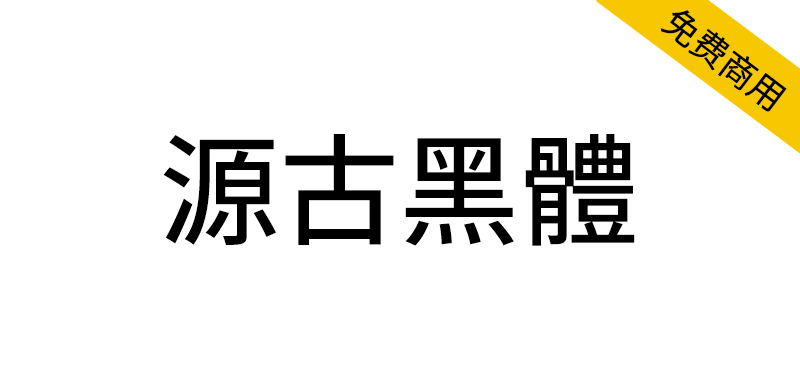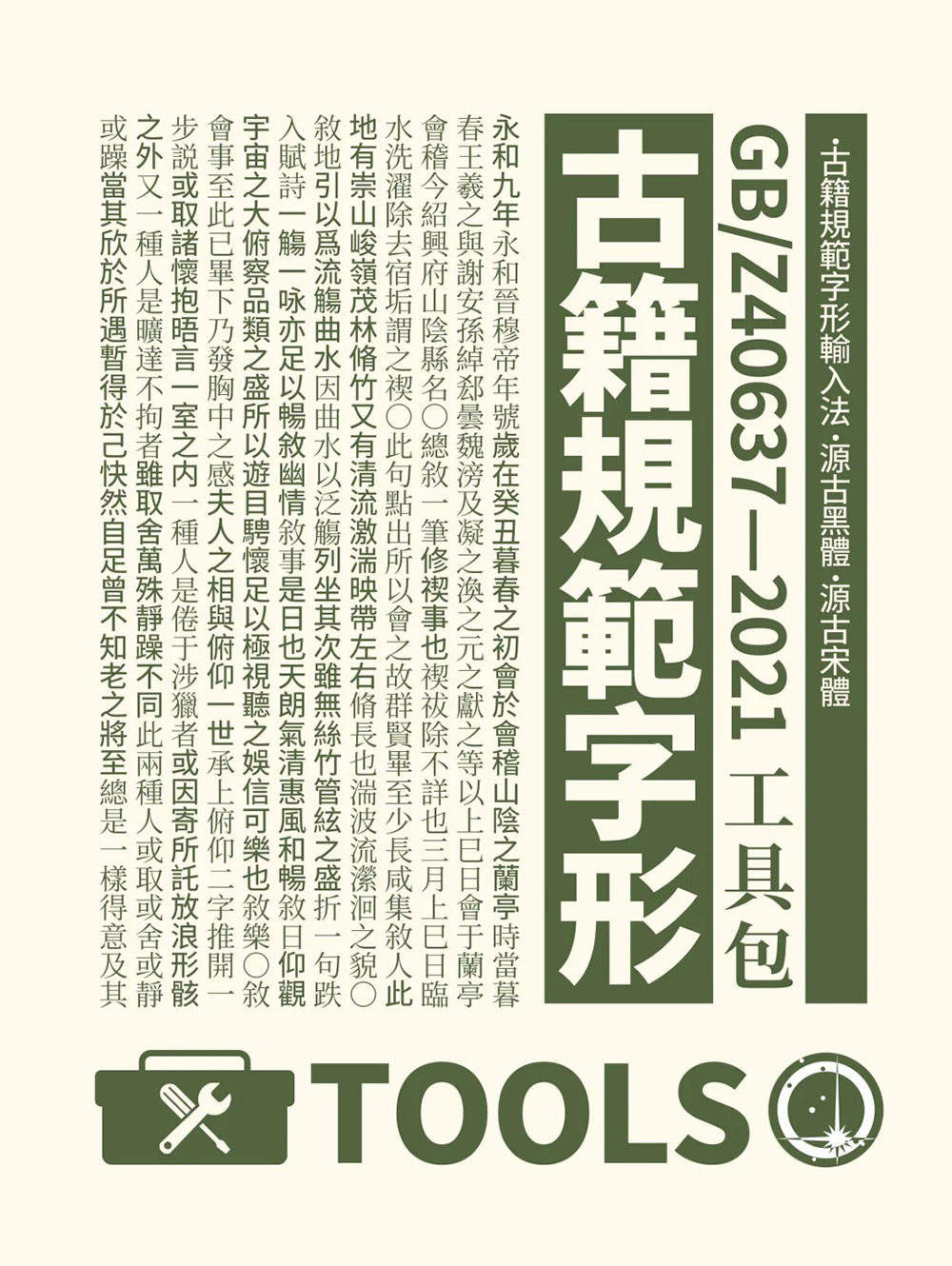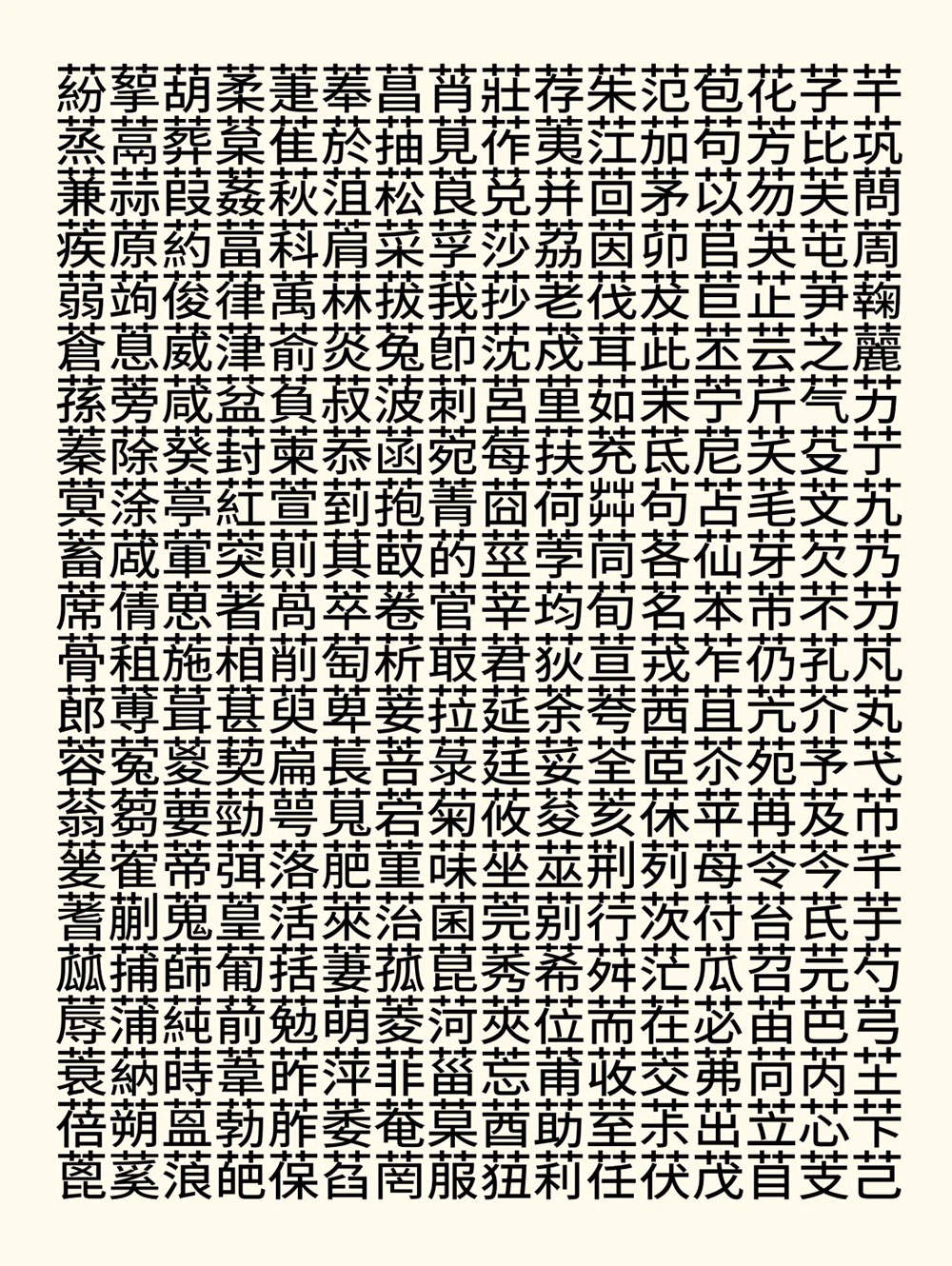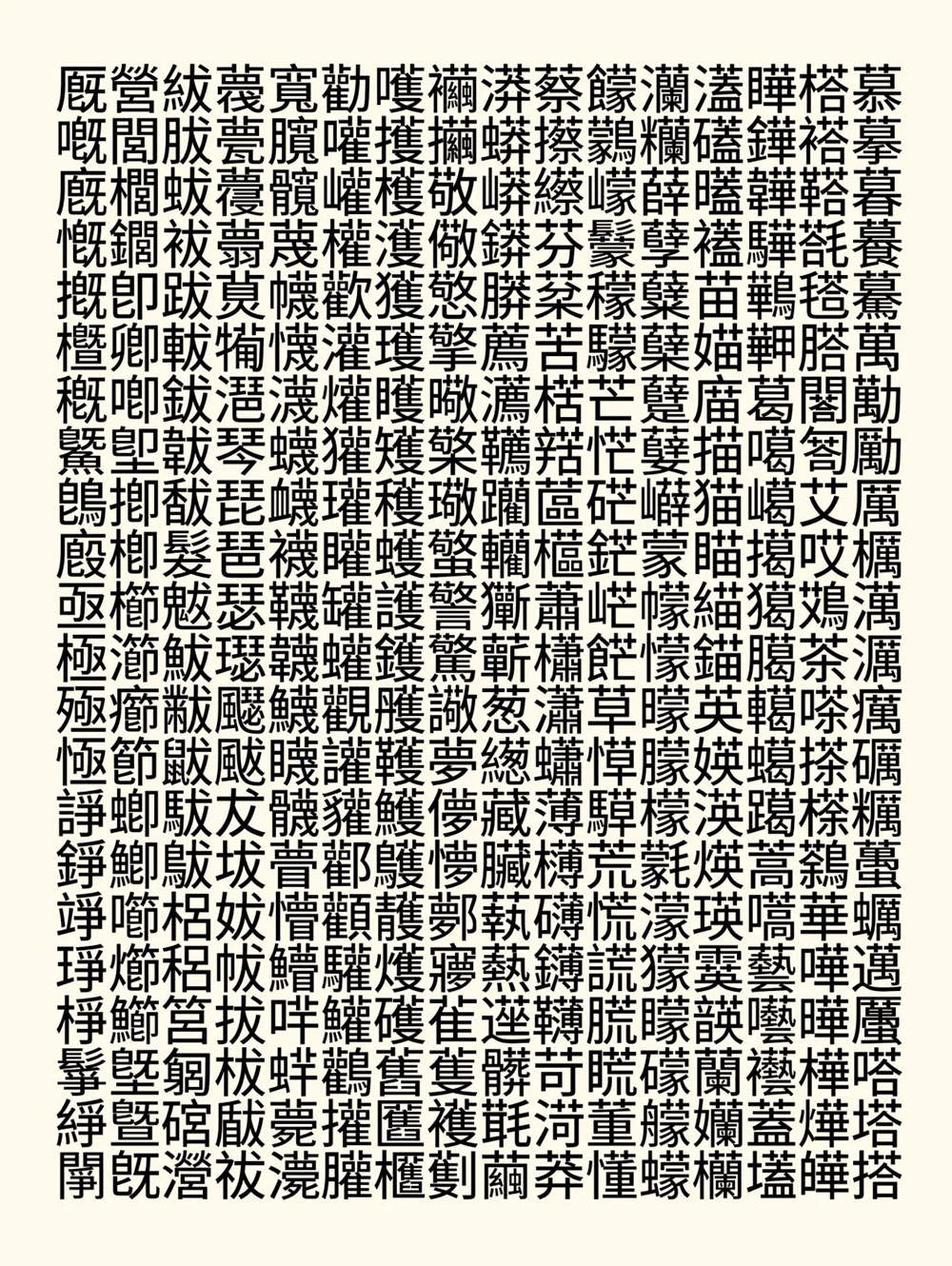
根据《古籍印刷通用字规范字形表》(简称“古籍表”)校改的思源黑∥宋体,以及配套输入法。《古籍表》作为大陆地区最新的繁体字字形标准,却迟迟没有相关的配套字体和输入法可用。于是就想着先自己手搓了一个(也为以后炼丹做个准备),希望能抛砖引玉,让很多人了解并使用起来。
古籍印刷通用字规范字形表:这个《古籍表》是在北京师范大学资深教授王宁先生的带领下,以汉字学科学理论为指导,以我国第一部大型辞书《辞源》所收文言词汇为切入点,在对海量古籍数字化资源进行统计测查基础上,确立严谨、科学的规范原则和验证条例,按照定字数、定主形、定笔数、定字音、定编码的“五定”目标,历时6年研制完成的。这是新中国成立以来对传世古籍印刷字的第一次整理规范。
该标准规定了古籍印刷通用字收字和宋体字形规范原则,给出了14250个古籍印刷通用字的字形、字音以及在国际编码字符集ISO/IEC 10646中的码位,适用于传世古籍的印刷出版,以及现代书刊的繁体版印刷。该标准的发布实施,对于推动语言文字规范化标准化信息化,传承弘扬中华优秀传统文化,建设社会主义文化强国都具有重要促进作用。
用不太准确但最容易理解的话说:此表是我国大陆地区第一个正式的繁体字规范。我愿称之为真·国标繁体。
2、然后是字体,这我老本行了,可谓轻车熟路。这次我一下做了两种,一种黑体一种宋体。
源古黑体基于思源黑体改造,扩B区的字取自遍黑体;源古宋体基于思源宋体改造,扩B区的字取自文津宋体。
得益于思源丰富的地区字形,拆拆凑凑很方便就可以改出一个古籍表版本。而关于那些部件不统一的字,我有选择性地擅自进行了统一。
然后黑体和宋体各提供了两个版本,一个是仅包含古籍表表内字的纯古籍表版,一个是把古籍表外的——思源本来有的那些字一股脑放进去的“F”版本(当然这些表外字就没有按古籍表规范修改,保持思源原样)。
各位可以按需选用。日常看书写东西可以用F版,确保不缺字。如果要作为做字体的参考或者炼丹的底子,就可以用纯古籍表版,以免被表外字误导。(没错,其实这次弄这俩字体,本来就是作为炼丹工具性质的)
除了这些“鱼”,我还准备了一些“渔”:我把我做字体时用到的、总结的各种字表都放在了包里。各位做字同仁可对照这些表,把自己的国标字体改造成古籍表标准。